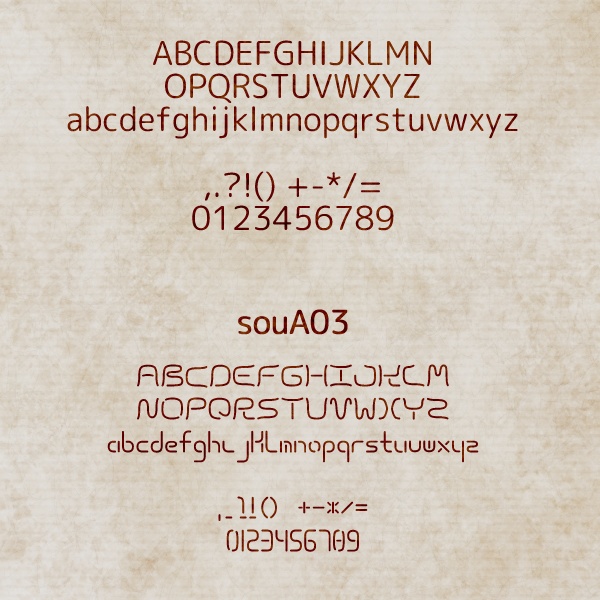
シンプルフォント「souA03」
丸みを帯びたステンシルっぽいフォント(OpenTypeフォント)です。 大文字は全角幅とし、印鑑・落款で漢字などと同じように 使えればと思いながら作成しました。 小文字も基本的に一律幅です。 【注意事項】 著作権は放棄しておりません。 意匠・商標登録などに使用することはご遠慮ください。 フォントデータの販売・再配布もご遠慮ください。 その他の使用についてはご自由に。 また、当フォントの使用により損害などが生じても、 一切の責任を負いませんのでご了承ください。 【タイプ可能な文字】 ABCDEFGHIJKLMNOPQRSTUVWXYZ abcdefghijklmnopqrstuvwxyz 0123456789,.?!()+-*/=